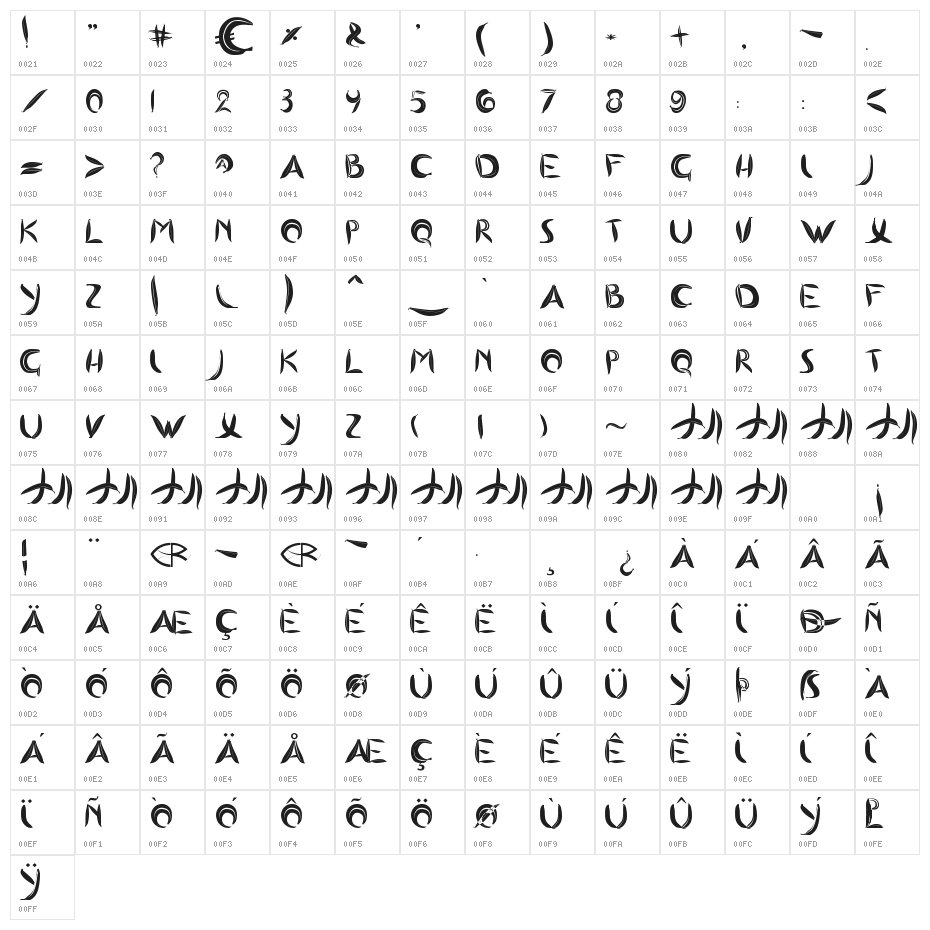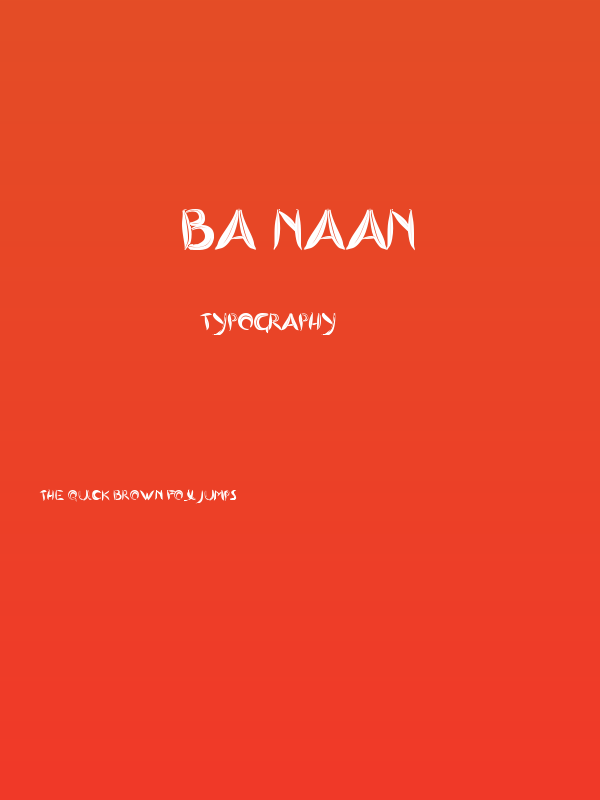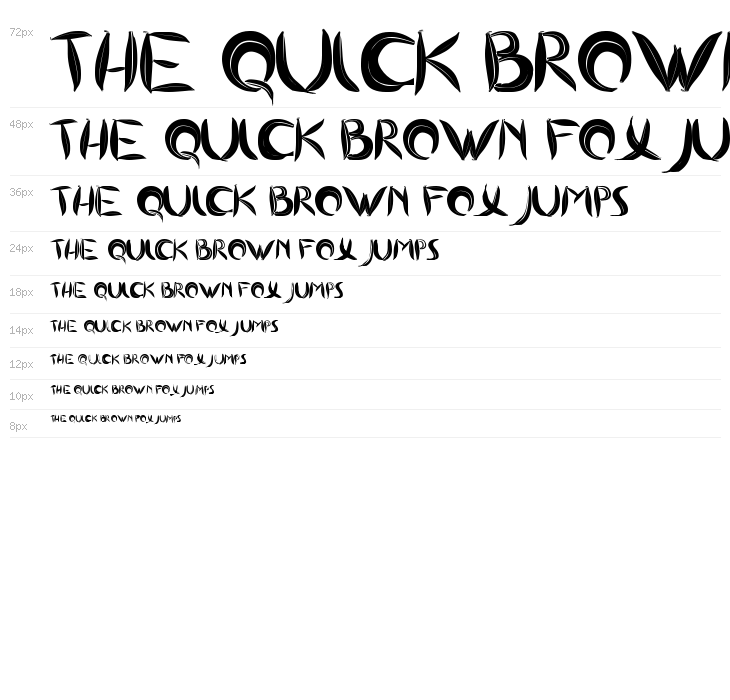
BA naan Font
✎ Calligraphic
| Anwendungsfall | Logos, Headlines, Posters |
| Vorgeschlagene Projekte | Ideal for branding, posters, album covers, and any project requiring a bold, artistic touch. |